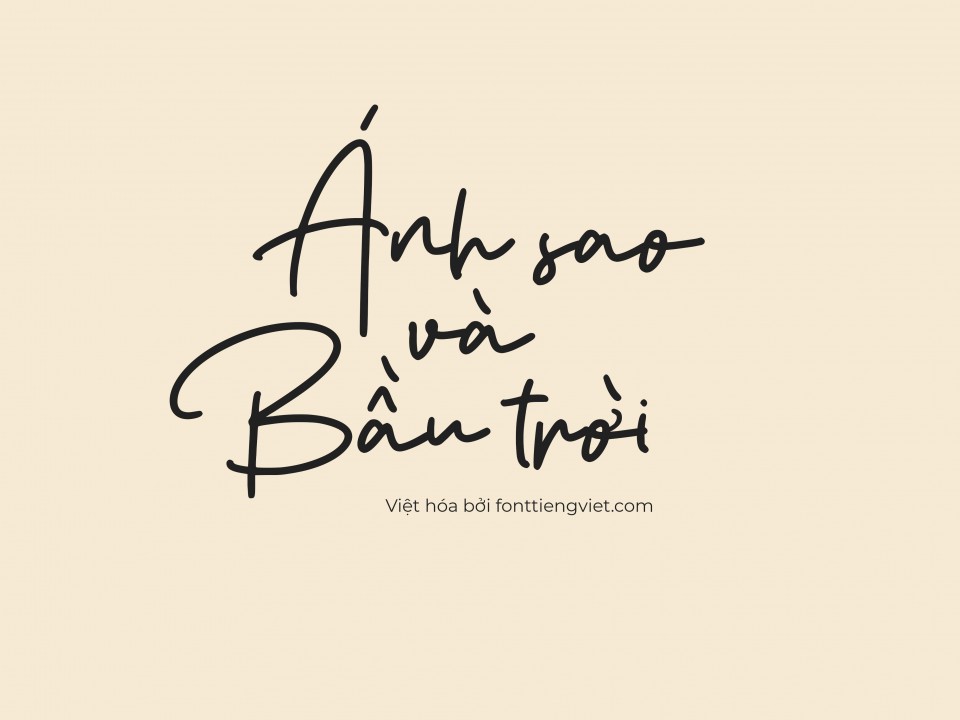
Font việt hóa 1FTV De Orleans
Giới thiệu về bộ Font việt hóa 1FTV De Orleans
Trong thế giới thiết kế đồ họa, việc lựa chọn một bộ Font Miễn Phí chất lượng luôn là ưu tiên hàng đầu của các nhà sáng tạo. Font việt hóa 1FTV De Orleans nổi lên như một biểu tượng của sự sang trọng, mang đậm phong cách vintage pha chút lãng mạn của nước Pháp thế kỷ 18. Đây là bộ phông chữ được tinh chỉnh kỹ lưỡng để phù hợp hoàn toàn với bảng mã tiếng Việt, giúp bạn dễ dàng sử dụng trên các phần mềm thiết kế phổ biến hiện nay.
Đặc điểm nổi bật của Font việt hóa 1FTV De Orleans
Nét chữ thanh lịch và linh hoạt
Đặc trưng lớn nhất của Font việt hóa 1FTV De Orleans chính là những đường nét bay bổng, uốn lượn tự nhiên như được viết bằng bút mực thủ công. Khoảng cách giữa các ký tự được tính toán khoa học, đảm bảo tính thẩm mỹ cao mà vẫn giữ được sự rõ ràng, dễ đọc cho người xem. Các dấu câu tiếng Việt được đặt vị trí chuẩn xác, không bị đè nét hay lệch hàng.
Ứng dụng đa dạng trong thiết kế
Bộ phông chữ này cực kỳ phù hợp cho các dự án thiết kế thiệp cưới, bao bì sản phẩm cao cấp, hay các tiêu đề bìa sách mang phong cách cổ điển. Ngoài ra, bạn cũng có thể sử dụng nó để làm logo cho các thương hiệu thời trang hoặc quán cà phê theo lối tối giản nhưng tinh tế. Khả năng tương thích tốt giúp nó vận hành mượt mà trên cả máy tính lẫn các thiết bị di động.